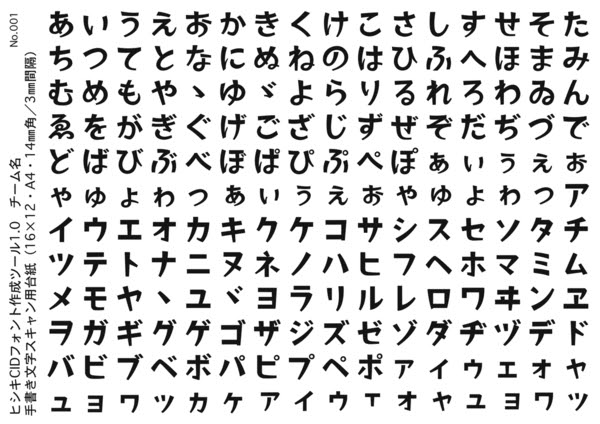
Японские символы ➡️ Конвертер японских символов
Японские символы.
Японские символы. Если вам нужно больше альтернатив для декорированного текста, просто нажмите «загрузить больше шрифтов». Альтернативы, которые появляются здесь, более случайны, немного отходят от стандартных и смешивают ресурсы, у которых мало общего, смайлики и символы.
Японские символы.
Этот шрифт имеет буквенный дизайн в виде кисти, который придает ему рукописный вид. Он идеально подходит для создания заголовков и текста с дизайном, очень похожим на японскую типографику.
Шрифт включает глифы с сочетанием этнических и культурных элементов, что придает шрифту уникальную эстетику.